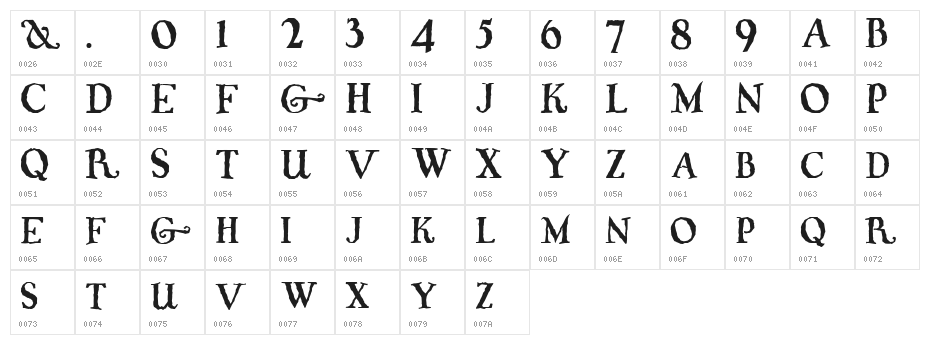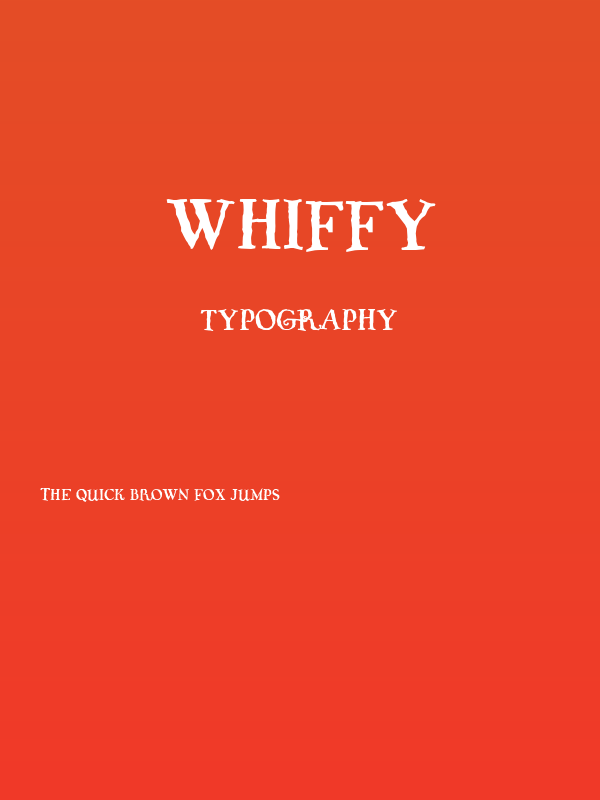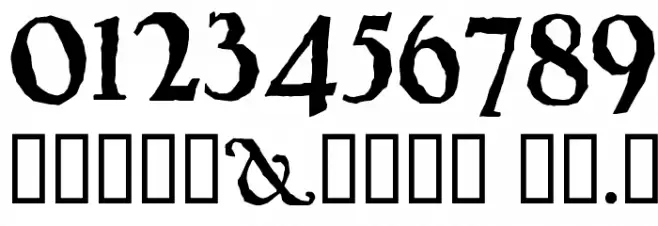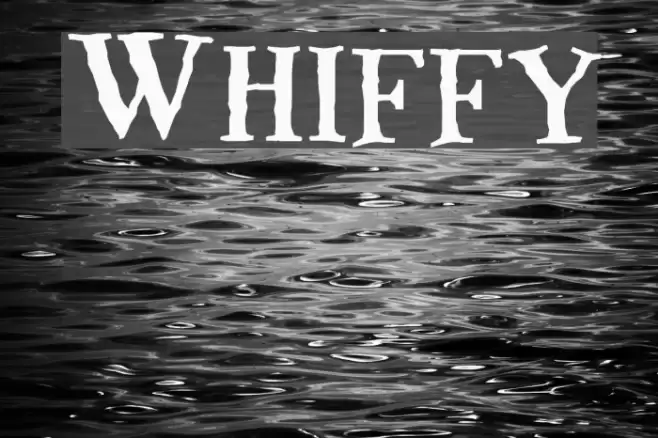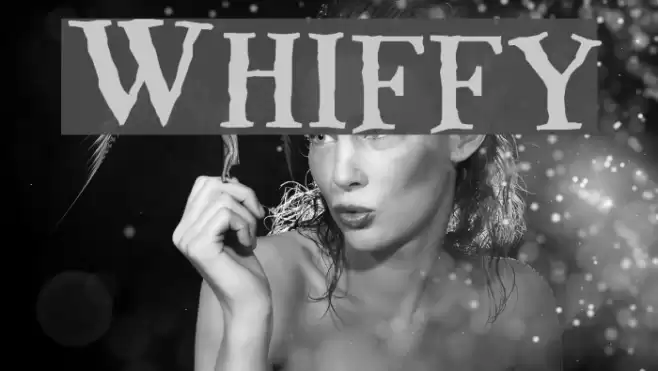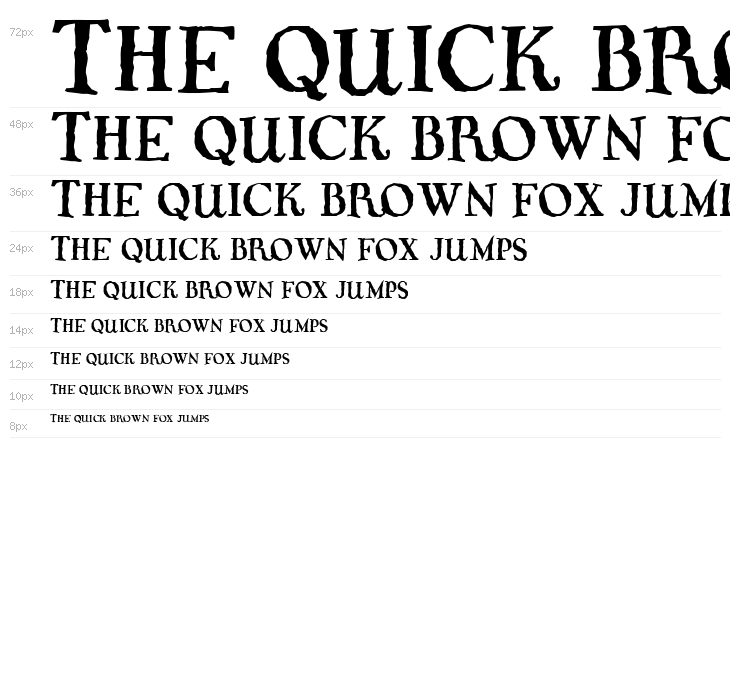
Whiffy Font
| Proiecte propuse | Ideal for projects requiring a dramatic or historical touch, such as book covers, posters, or themed event invitations. |